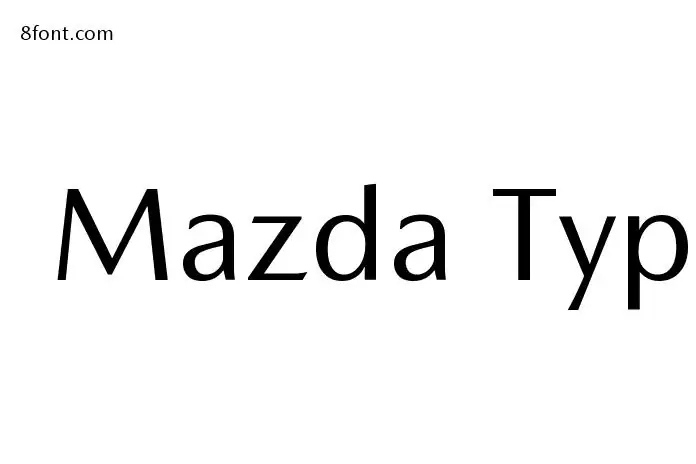
Mazda Type Font Là Gì? Tổng Tất Tần Tật Về Font Chữ Trên Hệ Thống Mazda
Từ khóa “Mazda type font” thường được người dùng tìm kiếm khi muốn hiểu rõ về font chữ được sử dụng trong hệ thống thông tin giải trí (infotainment) và cụm hiển thị (cluster) của các mẫu xe Mazda. Đây là một chủ đề kỹ thuật cụ thể, liên quan trực tiếp đến trải nghiệm người dùng (UX) và giao diện người-máy (HMI) trên xe. Bài viết này sẽ phân tích chuyên sâu về đặc điểm, mục đích, và sự phát triển của font chữ trong thiết kế nội thất Mazda, hoàn toàn dựa trên thông tin kỹ thuật và triết lý thiết kế của hãng.
Tóm Tắt Nhanh Các Điểm Chính
1. Mazda không công bố tên font chữ cụ thể dưới dạng thương hiệu thông thường (như Arial, Helvetica). Đó là một font chữ custom (tùy chỉnh) được thiết kế riêng bởi hoặc cho Mazda.
2. Mục tiêu chính: Đảm bảo tính dễ đọc (Readability)sự đồng bộ với ngôn ngữ thiết kế “Kodo – Soul of Motion” trên mọi cụm hiển thị.
3. Nguyên tắc thiết kế: Tập trung vào độ tương phản cao, độ đậm nhạt rõ ràng, và khoảng cách ký tự (kerning) tối ưu để đọc nhanh trong điều kiện ánh sáng khác nhau trên xe.
4. Phát triển theo thời hệ: Các thế hệ font chữ trên hệ thống Mazda Connect (từ phiên bản 1.0 đến 4.0) có sự tinh chỉnh về độ cong, độ dày và hình dạng chữ để phù hợp với độ phân giải màn hình và xu hướng thiết kế mới.
Giải Đáp Ngay: Font Chữ Trên Màn Hình Mazda Có Tên Gì?
Khi nhắc đến “Mazda type font”, câu hỏi đầu tiên thường là về danh tính của nó. Trên các diễn đàn kỹ thuật và trong tài liệu thiết kế, font chữ này thường được gọi chung là “Mazda Type” hoặc “Mazda Font”. Đây là một font chữ sans-serif (không chân) được thiết kế riêng, không phải là một font phổ biến trên thị trường. Nó không được bán độc lập và là một phần của bản quyền thiết kế giao diện người dùng (UI/UX design system) của Mazda. Sự lựa chọn này phản ánh triết lý của Mazda: tạo ra một trải nghiệm thương hiệu nhất quán và độc đáo, ngay cả trong chi tiết nhỏ như kiểu chữ.
Đặc Điểm Thiết Kế Cơ Bản Của Font Chữ Mazda
Font chữ này được tối ưu hóa cho mục đích sử dụng trong xe hơi, dẫn đến những đặc điểm nổi bật sau:
• Độ Tương Phản Cao: Các nét chữ (stroke) được thiết kế với độ dày cân đối, đảm bảo chữ sắc nét, không bị mờ hoặc “chảy” khi nhìn từ các góc độ khác nhau trong xe, đặc biệt khi xe đang di chuyển.
• Khoảng Trống Rộng (Open Counter): Phần khoảng trống bên trong các ký tự như ‘a’, ‘o’, ‘e’ được mở rộng. Điều này giúp các chữ nhận diện nhanh hơn, giảm tình trạng “đóng chung” với các chữ liền kề, rất quan trọng khi tài xế chỉ có thời gian ngắn để liếc màn hình.
• Độ Cao Xác Định: Chiều cao của các chữ cái (x-height) được tính toán kỹ, giúp các chữ cái thường (như ‘x’, ‘a’, ‘e’) dễ đọc và cân đối với các chữ hoa.
• Kerning Tối Ưu: Khoảng cách giữa các ký tự được hiệu chỉnh thủ công để tạo thành các cụm từ dễ đọc, tránh hiện tượng các chữ quá dính vào nhau hoặc cách xa quá mức.
• Không Có Chân (Sans-Serif): Đây là lựa chọn phổ biến cho giao diện kỹ thuật số vì chữ không chân thường hiện đại, sạch sẽ và dễ đọc trên màn hình với độ phân giải vừa phải.
Sự Phát Triển Của Font Chữ Qua Các Thế Hệ Hệ Thống Mazda Connect
Sự thay đổi về font chữ không diễn ra ngẫu nhiên. Nó song hành với sự phát triển của hệ thống infotainment Mazda Connect, cả về phần cứng (màn hình lớn hơn, độ phân giải cao hơn) và phần mềm (giao diện đơn giản hơn, tập trung vào nút bấm vật lý).
• Thế hệ 1.0 & 2.0 (Màn hình 7 inch, giao diện phức tạp hơn): Font chữ có thể có độ đậm đa dạng hơn, với một số kiểu chữ in nghiêng (italic) hoặc đậm (bold) để phân biệt các mục menu. Nó phản ánh giao diện đầy đủ chức năng, nhiều tầng menu.
• Thế hệ 3.0 (Màn hình 8.8 inch, thiết kế tối giản): Font chữ được tinh chỉnh lại, thường có độ đậm đồng đều hơnđường nét mềm mại hơn. Sự chuyển đổi này nhấn mạnh tính tối giản, dễ thao tác khi lái xe, phù hợp với triết lý “Jinba Ittai” (xe và người lái như một thể thống nhất).
• Thế hệ 4.0 (Màn hình lớn, tích hợp sẵn, giao diện dạng lưới – grid layout): Font chữ có thể được làm nhẹ (light) hoặc trung bình (regular) hơn, với khoảng cách dòng (line spacing) rộng hơn. Điều này tận dụng tối đa không gian màn hình lớn, giảm sự “BÃO THÔNG TIN” và giúp mắt người lái dễ theo dõi thông tin quan trọng như bản đồ, âm thanh.
Tại Sao Mazda Đầu Tư Vào Font Chữ Riêng?
Việc này không chỉ là “đẹp”. Đó là một quyết định chiến lược về An Toàn và Trải Nghiệm Người Dùng:
1. Giảm Tải Thị Giác: Một font chữ được tối ưu giúp não bộ xử lý thông tin nhanh hơn. Khi tài xế chỉ liếc màn hình 0.5 giây, một chữ dễ đọc sẽ truyền tải thông tin chính xác ngay lập tức.
2. Đồng Bộ Thương Hiệu: Từ logo, thiết kế ngoại thất, đến giao diện màn hình, mọi chi tiết đều tuân theo ngôn ngữ thiết kế Kodo. Font chữ là một phần không thể thiếu của sự đồng bộ đó, tạo cảm giác “xe Mazda” ngay cả khi bạn chỉ nhìn vào màn hình.